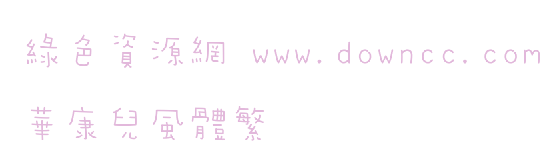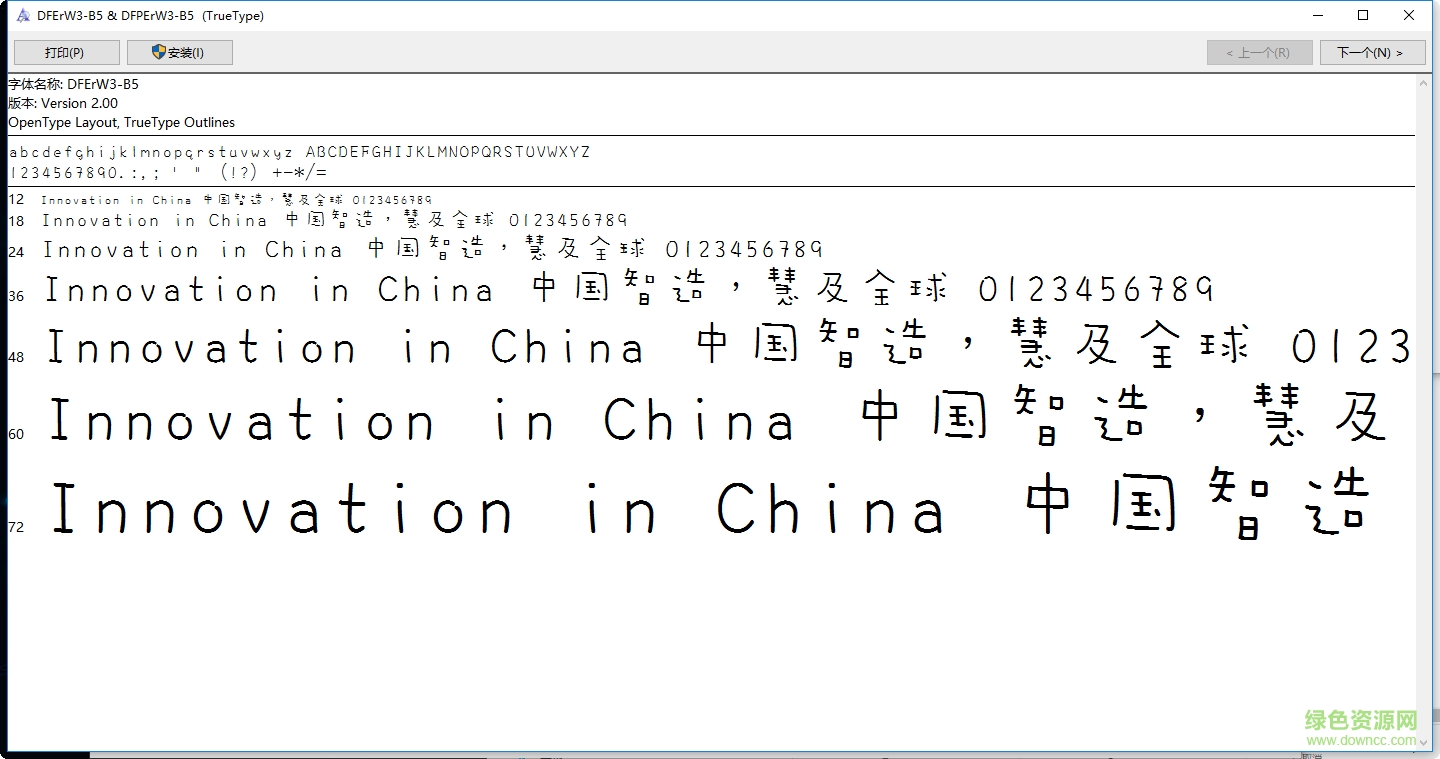
華康華綜體簡(jiǎn)是一款非常適合女生和小朋友的字體。這款字體方正小巧,非??蓯?ài)~歡迎來(lái)綠色資源網(wǎng)下載這款字體。
華康兒風(fēng)體下載,華康字體以其清新自然的設(shè)計(jì)、繼承也創(chuàng)新的完美結(jié)合、全球觀的推廣營(yíng)銷,使得其贏得相當(dāng)比例的用戶。